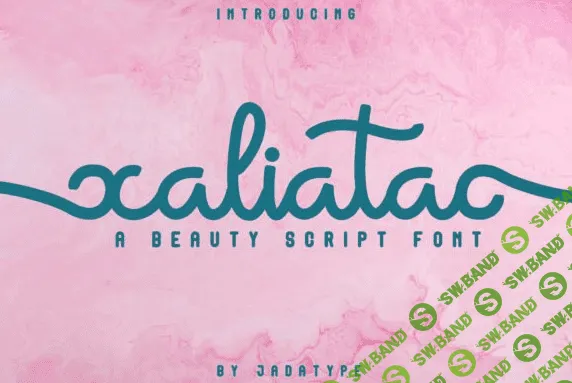
Название: Caliata Font
Калиста чувствует себя одинаково очаровательной и элегантной. Он выглядит потрясающе на свадебных приглашениях, благодарственных открытках, цитатах, поздравительных открытках, логотипах, визитных карточках и любом другом дизайне, который нуждается в рукописном прикосновении.